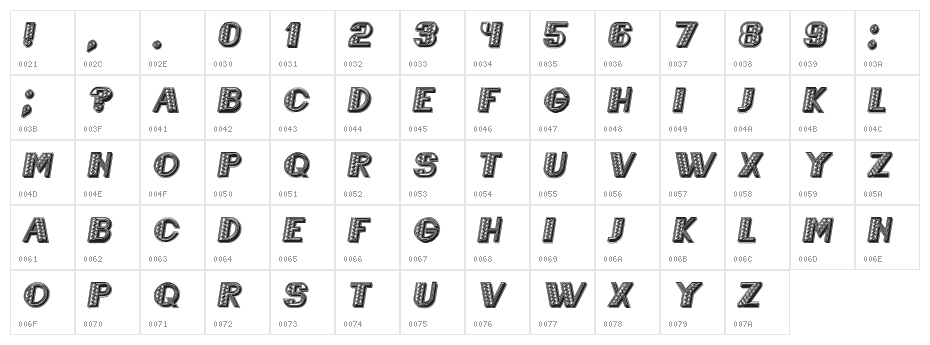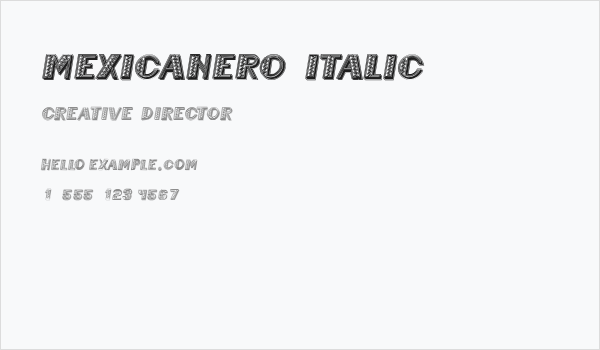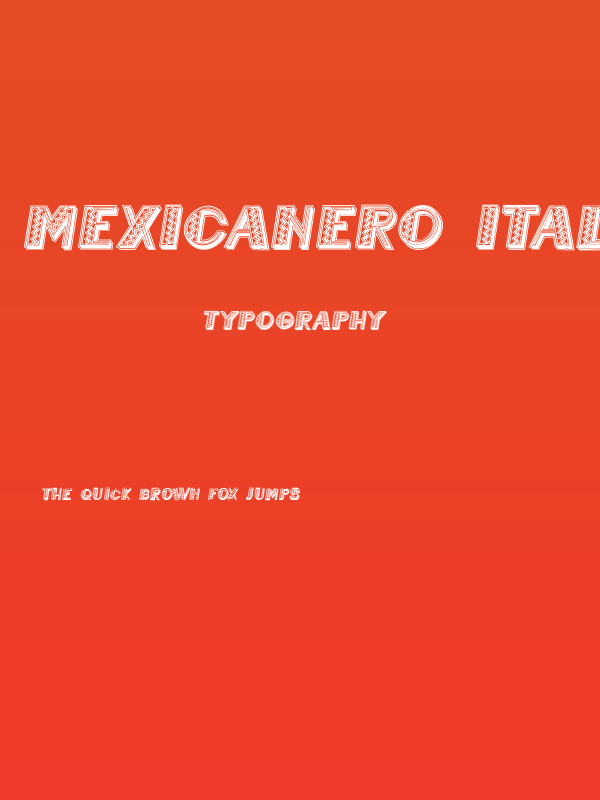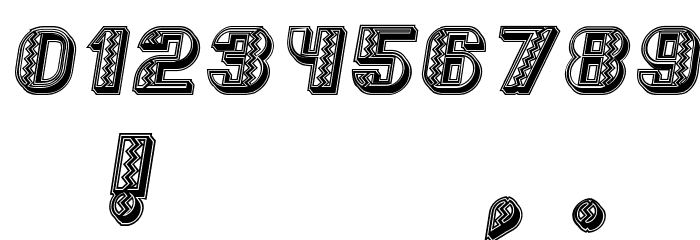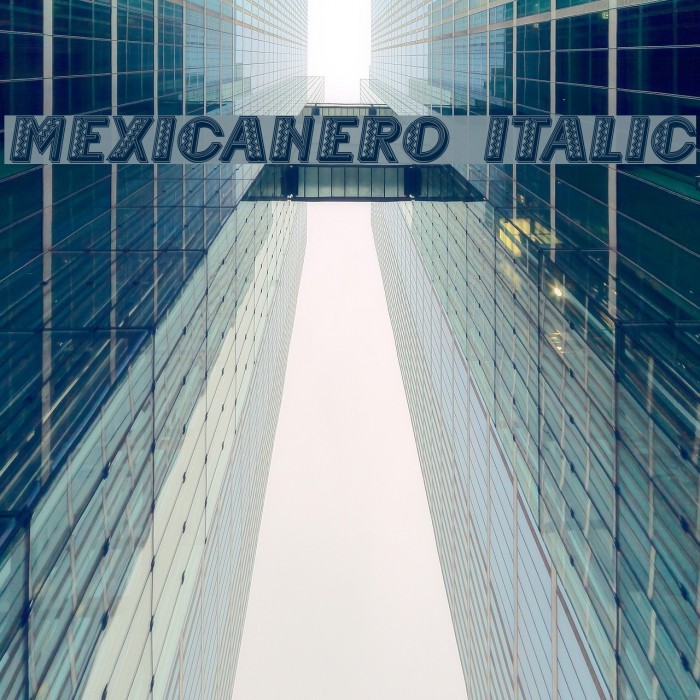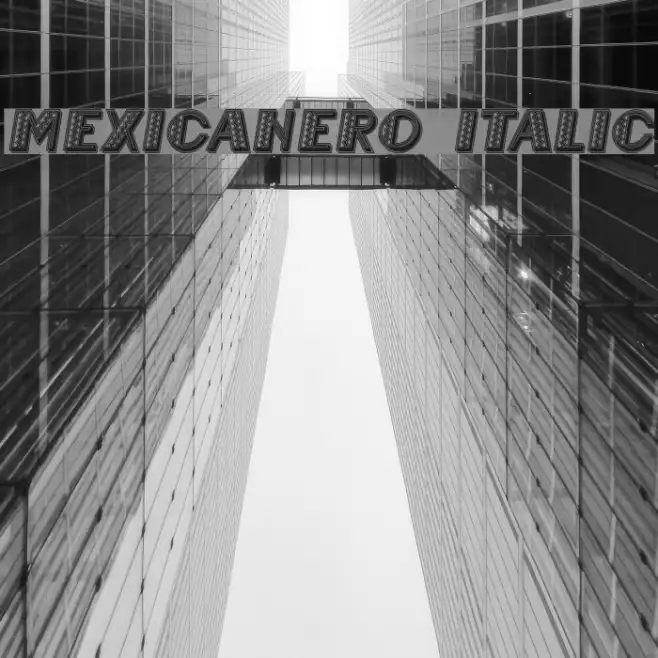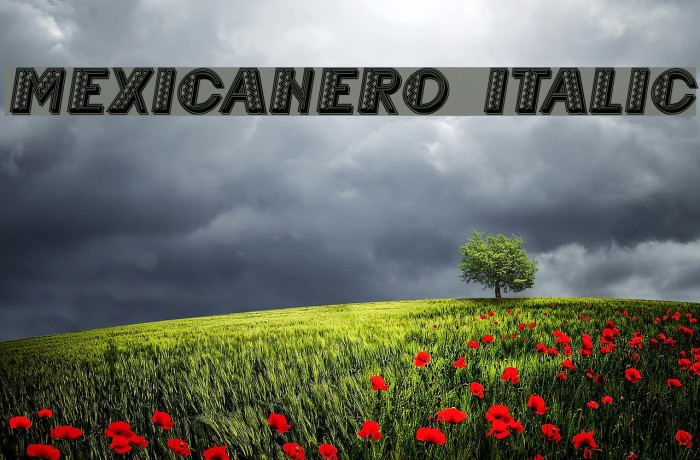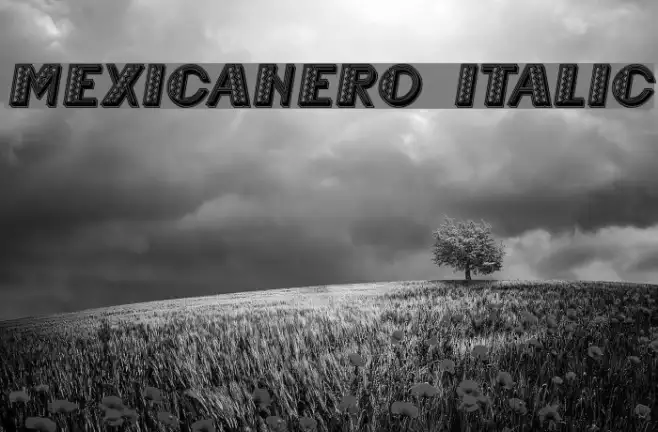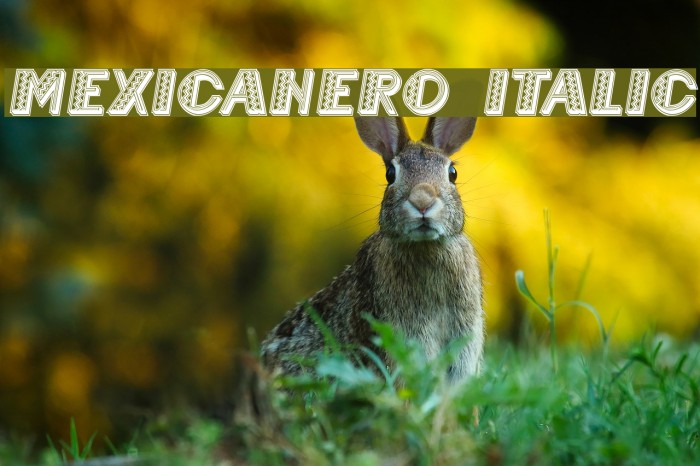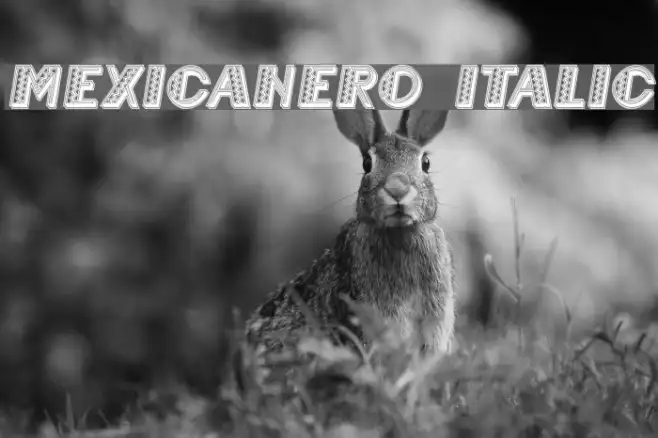
Mexicanero Italic Font
| Vorgeschlagene Projekte | Ideal for projects that require a bold and decorative touch, such as posters, event invitations, branding for cultural events, or any design needing a vibrant and artistic flair. |